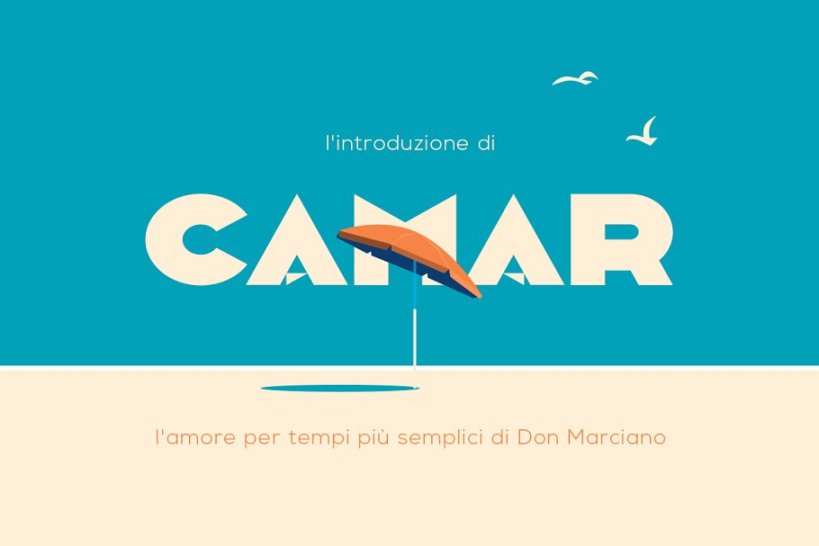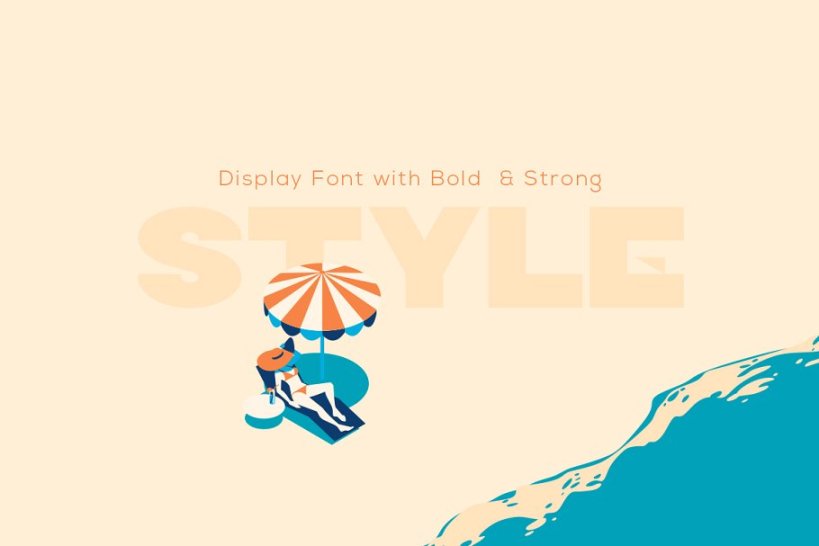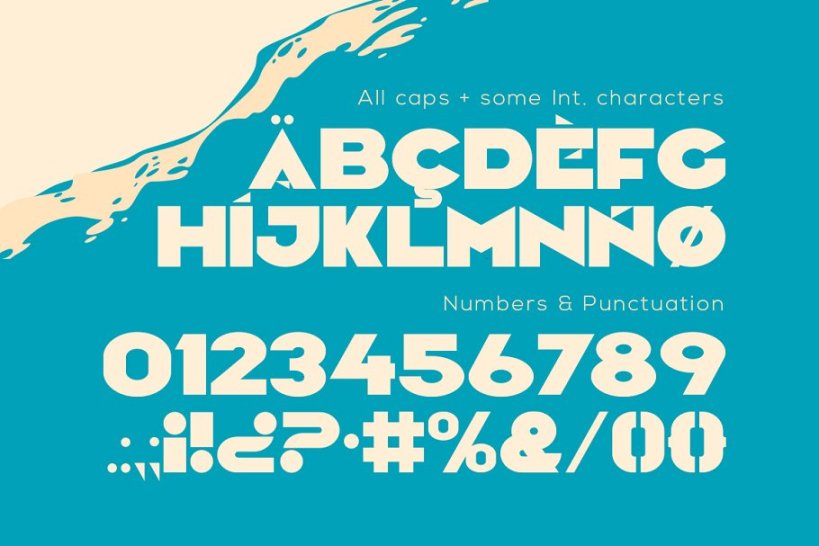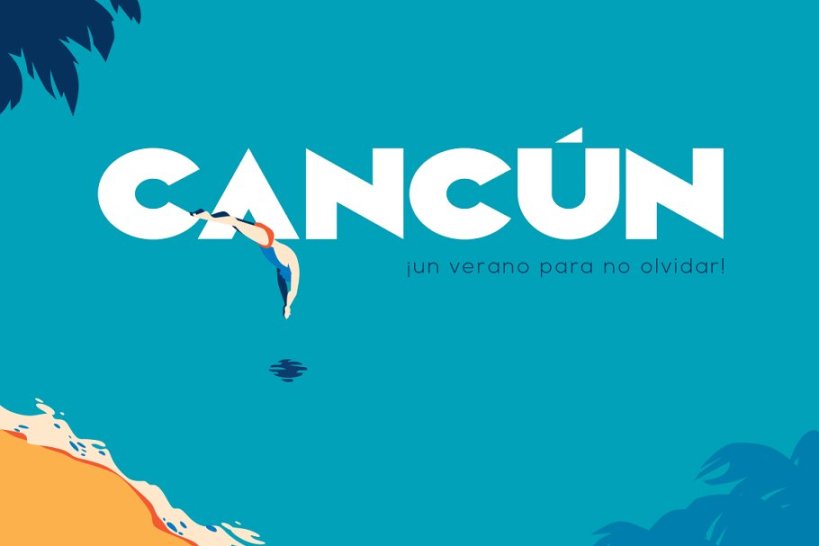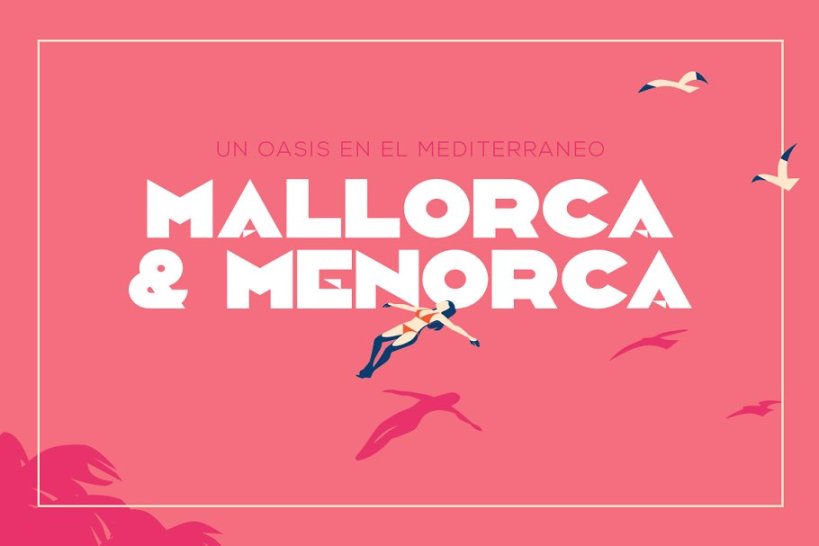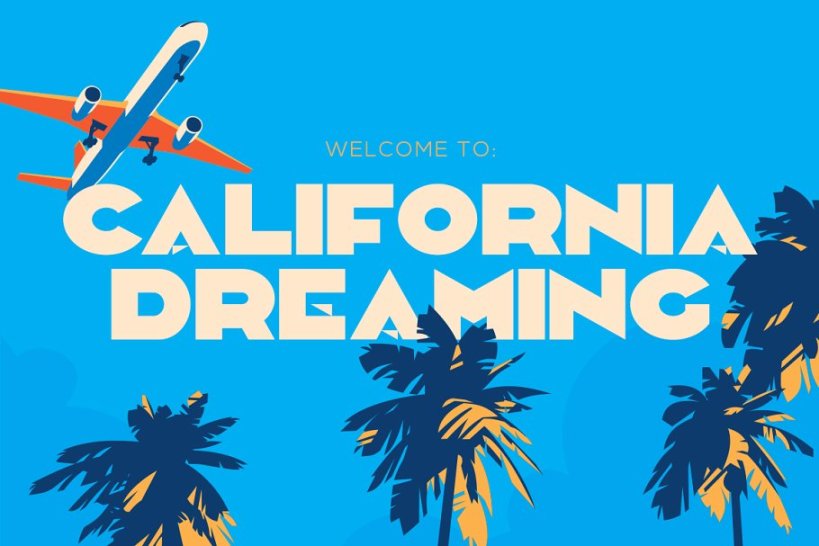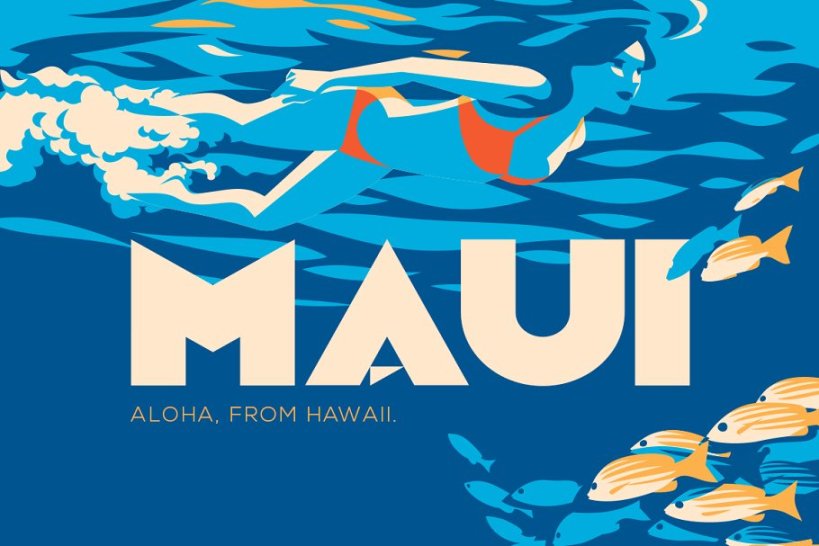
Typographie gratuite : Camar Vintage par Juan Miguel
Camar Vintage est une police d’inspiration Art Déco, créée par Juan Miguel. Conçue à l’origine pour un ensemble de cartes postales cette typo uniquement composée de majuscules simples et nettes conviendra parfaitement aux titres courts et forts. N’hésitez pas à la tester pour un usage personnel en la téléchargeant : ici. Et si elle vous plaît vraiment, vous pouvez acheter la typographie pour un très petit budget sur Creative Market : ici.